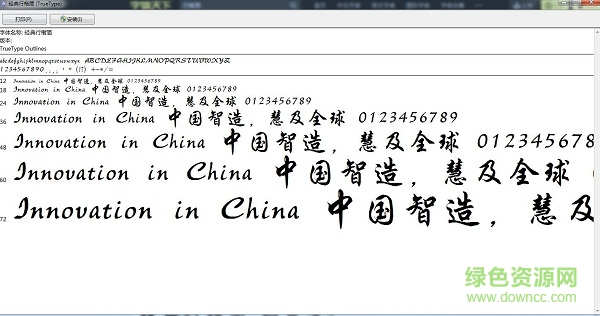
經(jīng)典行楷簡字體是一款瀟灑漂亮的行楷字體,用筆隨意,點(diǎn)畫勻稱呼應(yīng),有一種靈動的氣質(zhì),觀賞性與可讀性兼?zhèn)?,適用于書籍封面、影視海報等方面,需要朋友快來綠色資源網(wǎng)下載吧!
1.行楷書的字形是在楷書的點(diǎn)畫基礎(chǔ)上,略加變動而適于連筆書寫的一種實(shí)用性很強(qiáng)的書體。
2.行楷結(jié)字很自由,字的筆畫可依據(jù)不同連筆位置的需要作出靈活多樣的變化,書寫快捷,不需停筆、頓筆更長的時間。
3.行楷將楷書的體勢、點(diǎn)畫變得圓轉(zhuǎn)連帶、變化多樣。